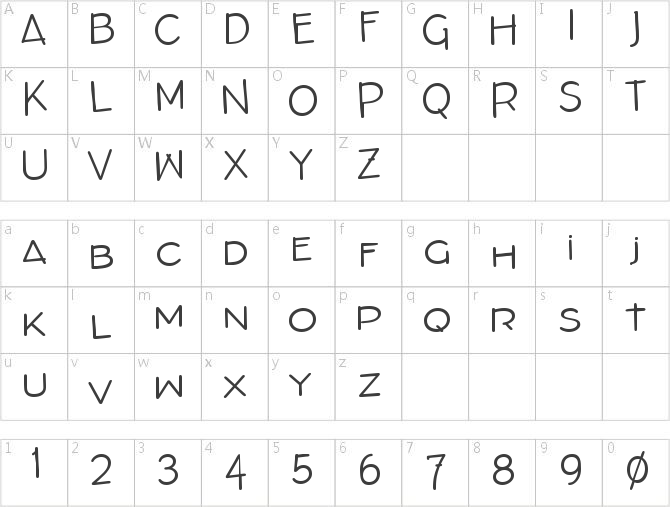
Architects Draft Bold 詳情頁
Architects Draft Bold字體字庫是一款讓人賞心悅目、百看不厭的英文字體,適合各類廣告和產(chǎn)品包裝設(shè)計應(yīng)用,字體大小0.04MB,格式為ttf字體,上傳用戶是快樂圍棋,作者/版權(quán)方為未知